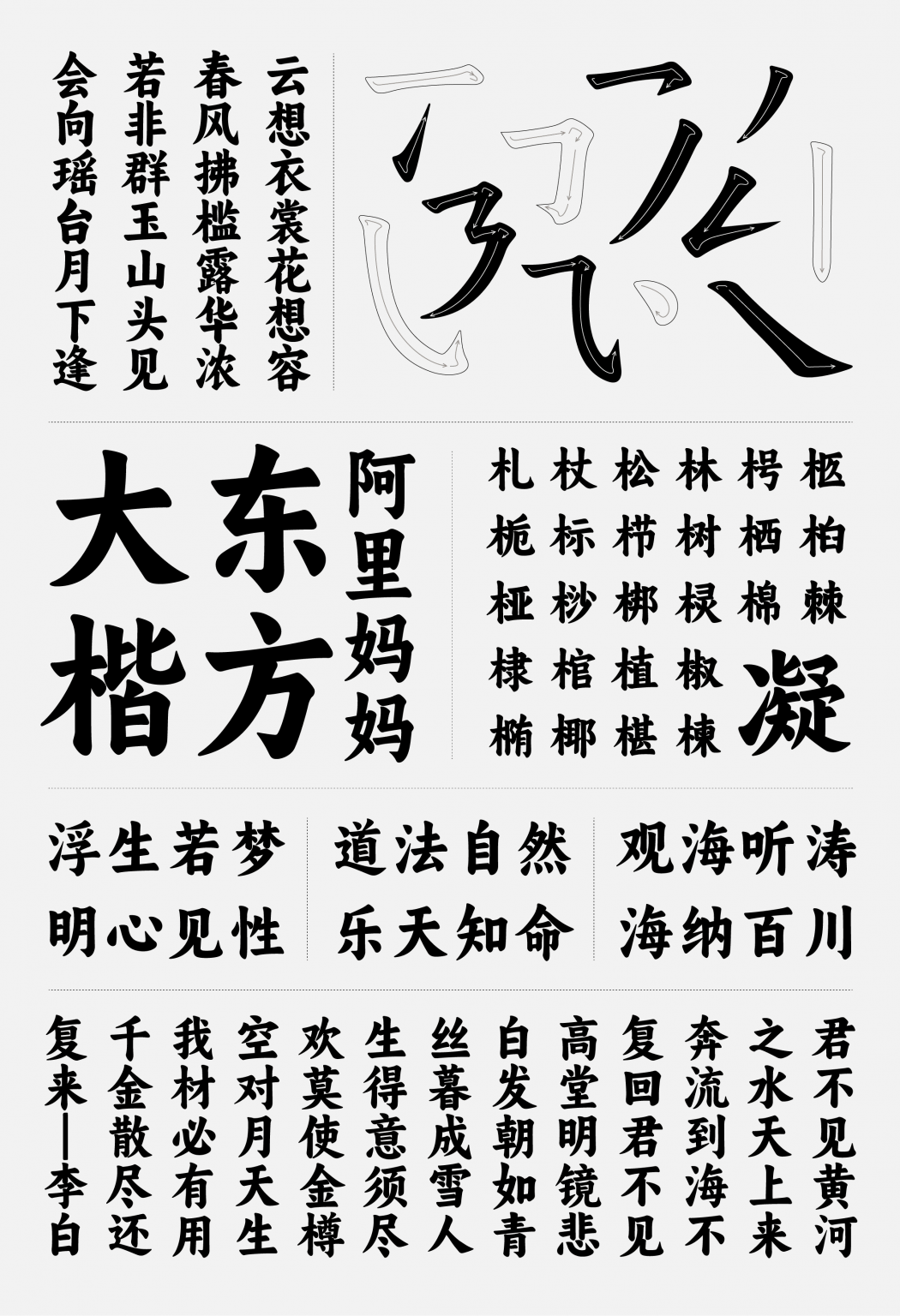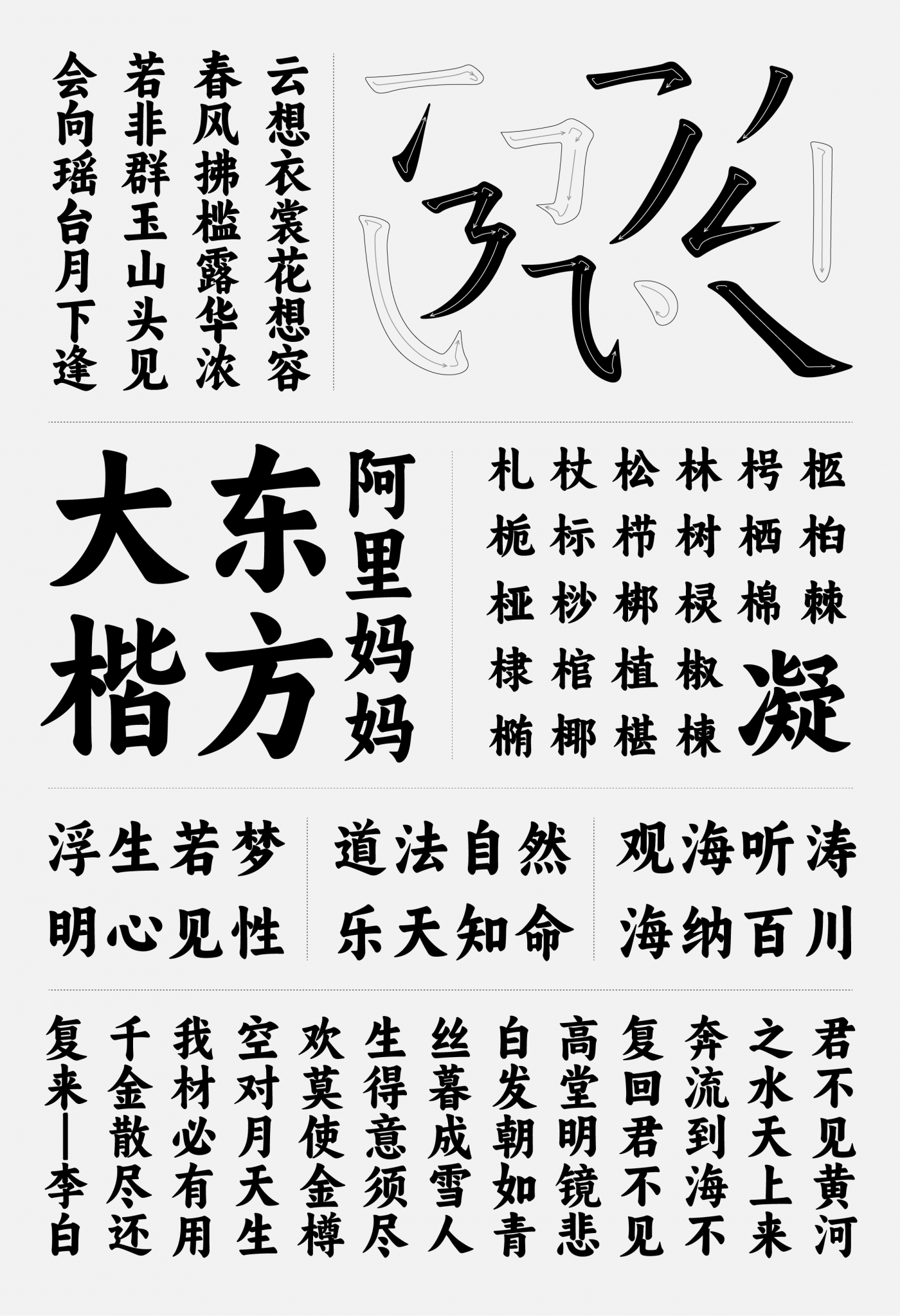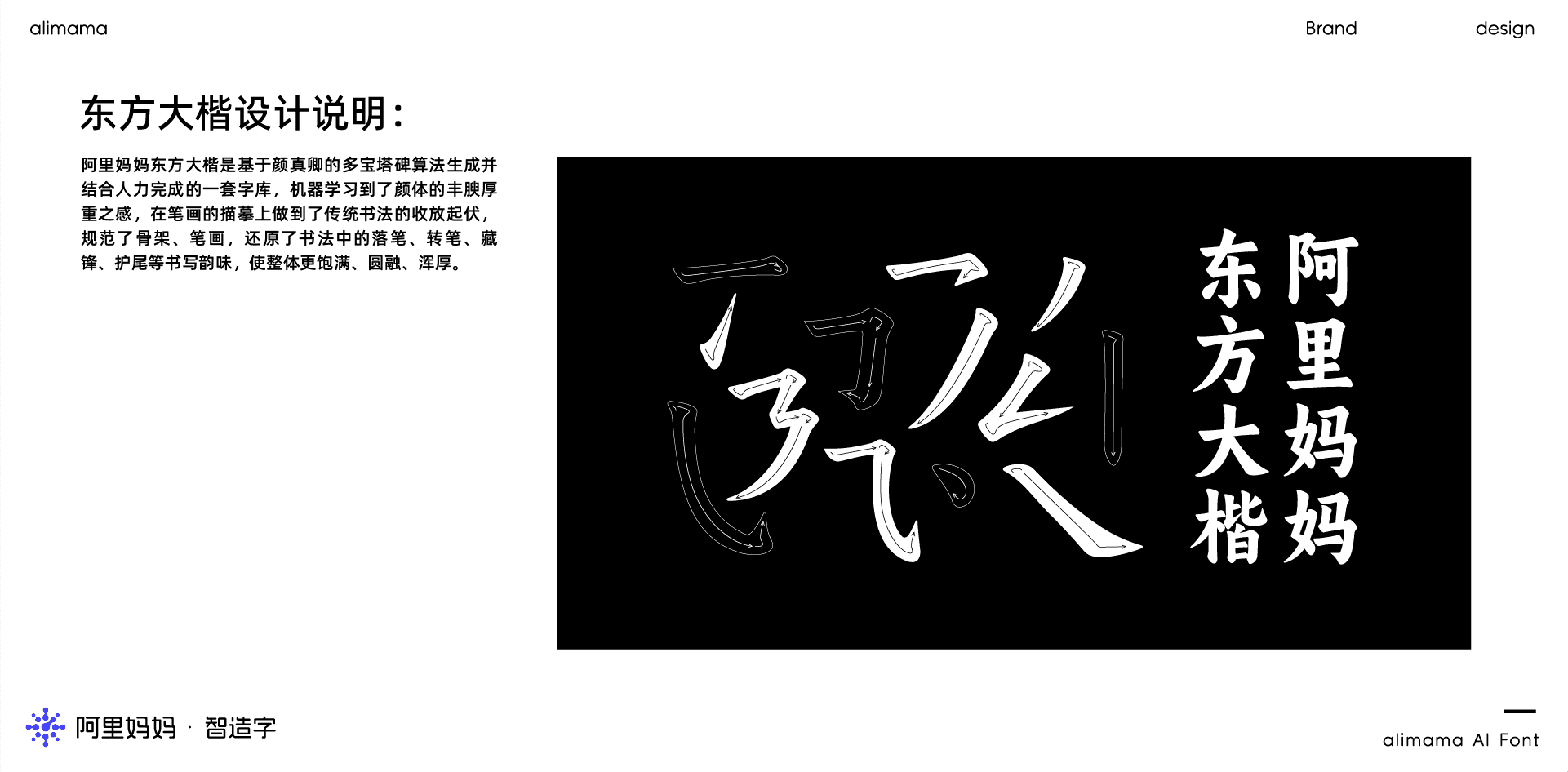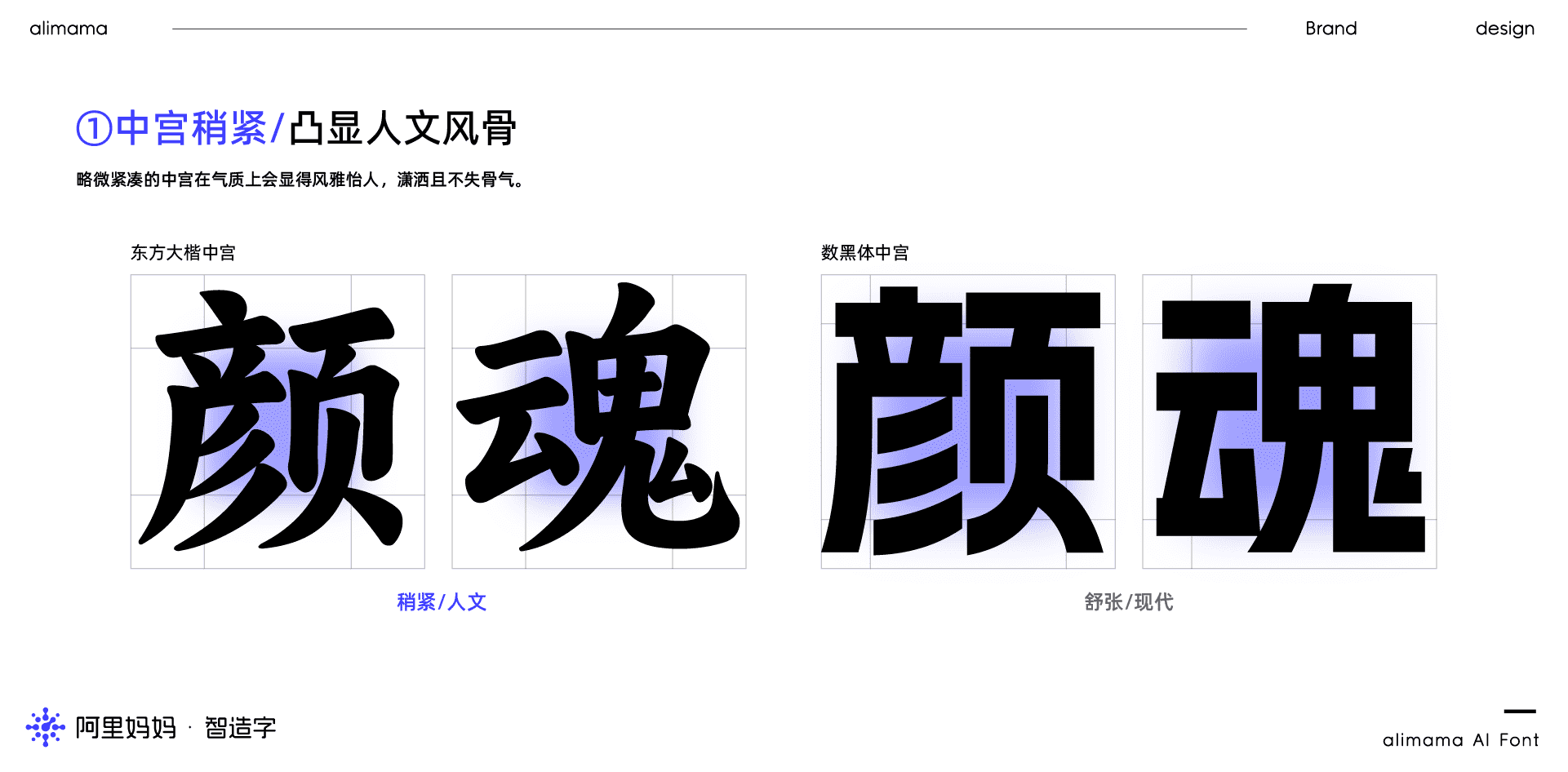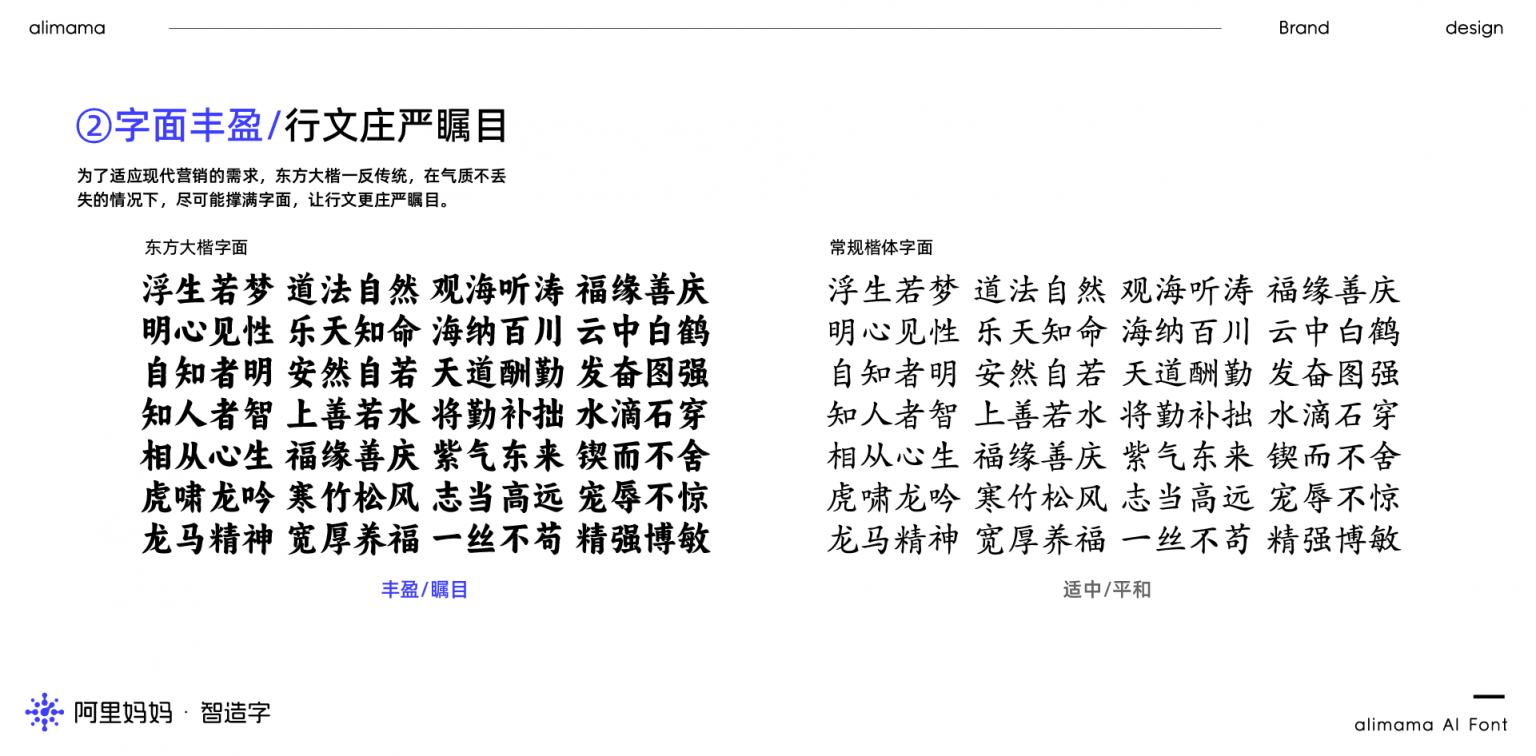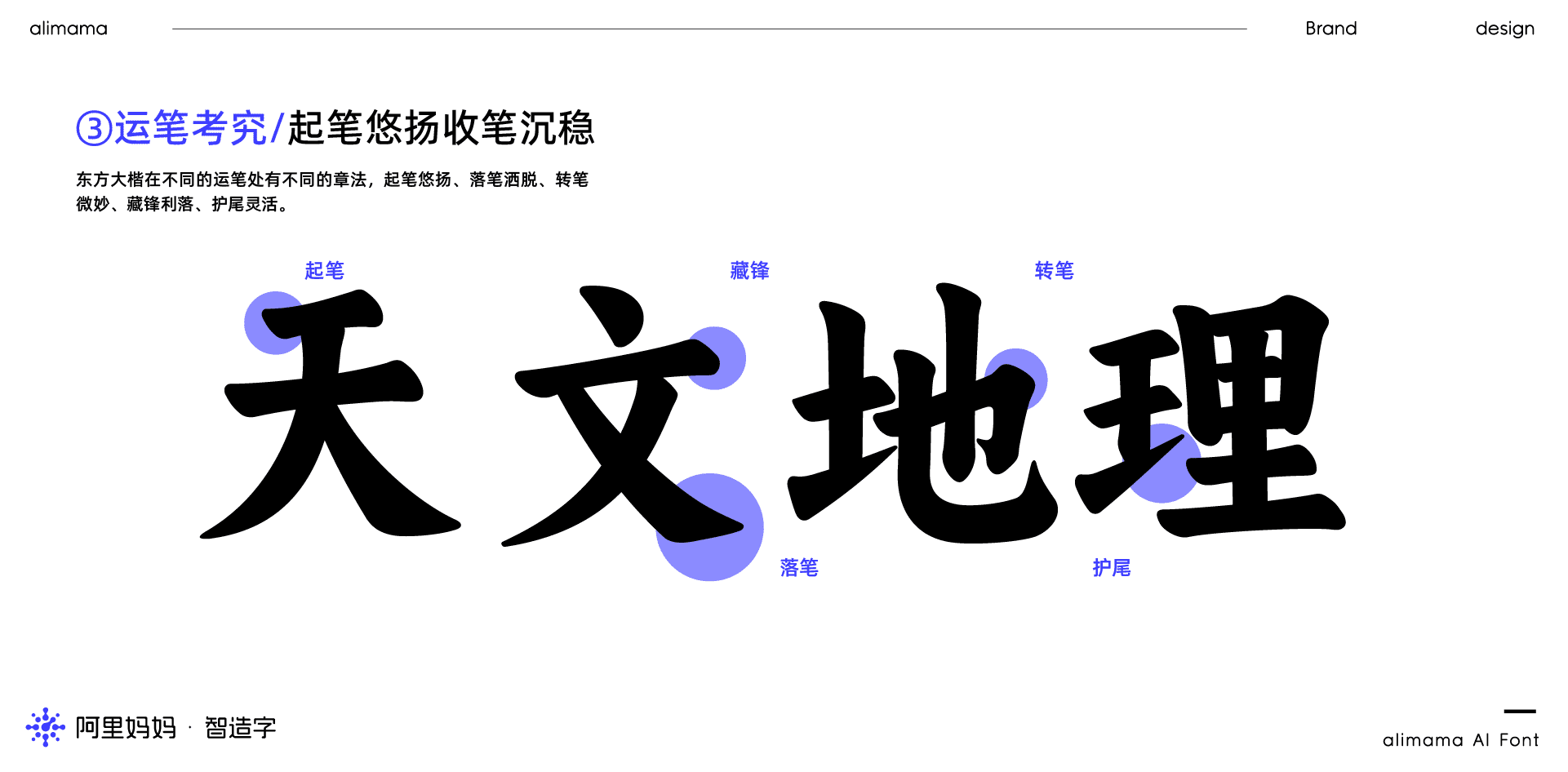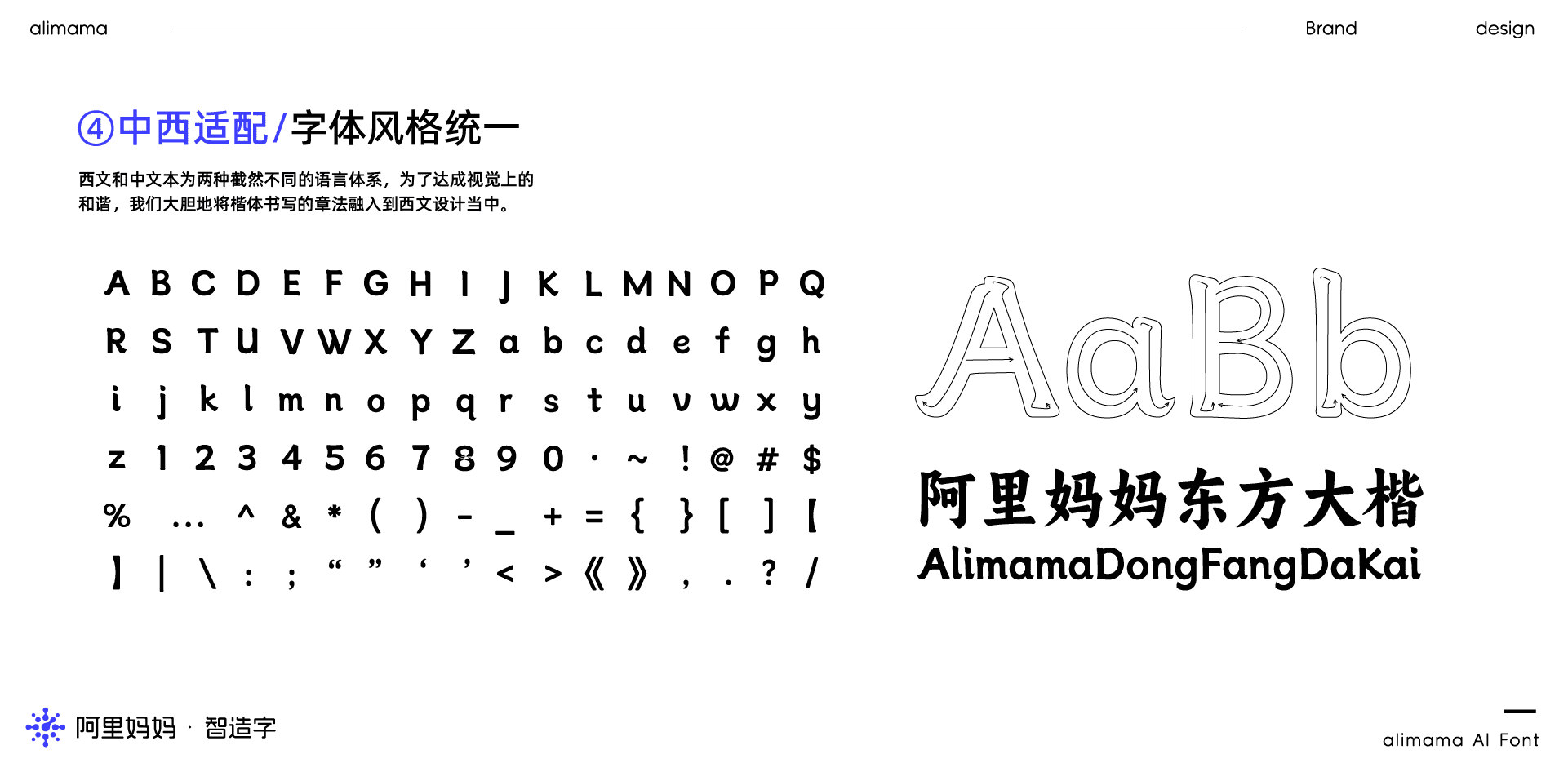
阿里妈妈东方大楷
字体风格: 楷书
阿里妈妈东方大楷是基于颜真卿的多宝塔碑算法生成并结合人力完成的一套字库,机器学习到了颜体的丰腴厚重之感,在笔画的描摹上做到了传统书法的收放起伏,规范了骨架、笔画,还原了书法中的落笔、转笔、藏锋、护尾等书写韵味,使整体更饱满、圆融、浑厚。
阿里妈妈东方大楷为中文简体字库,收纳的中文字符包括但不限于GB2312,共计6763个汉字;英文大小写(含全角、半角、合体字等)共105个;常用标点符号共175个,总计7043个字符。